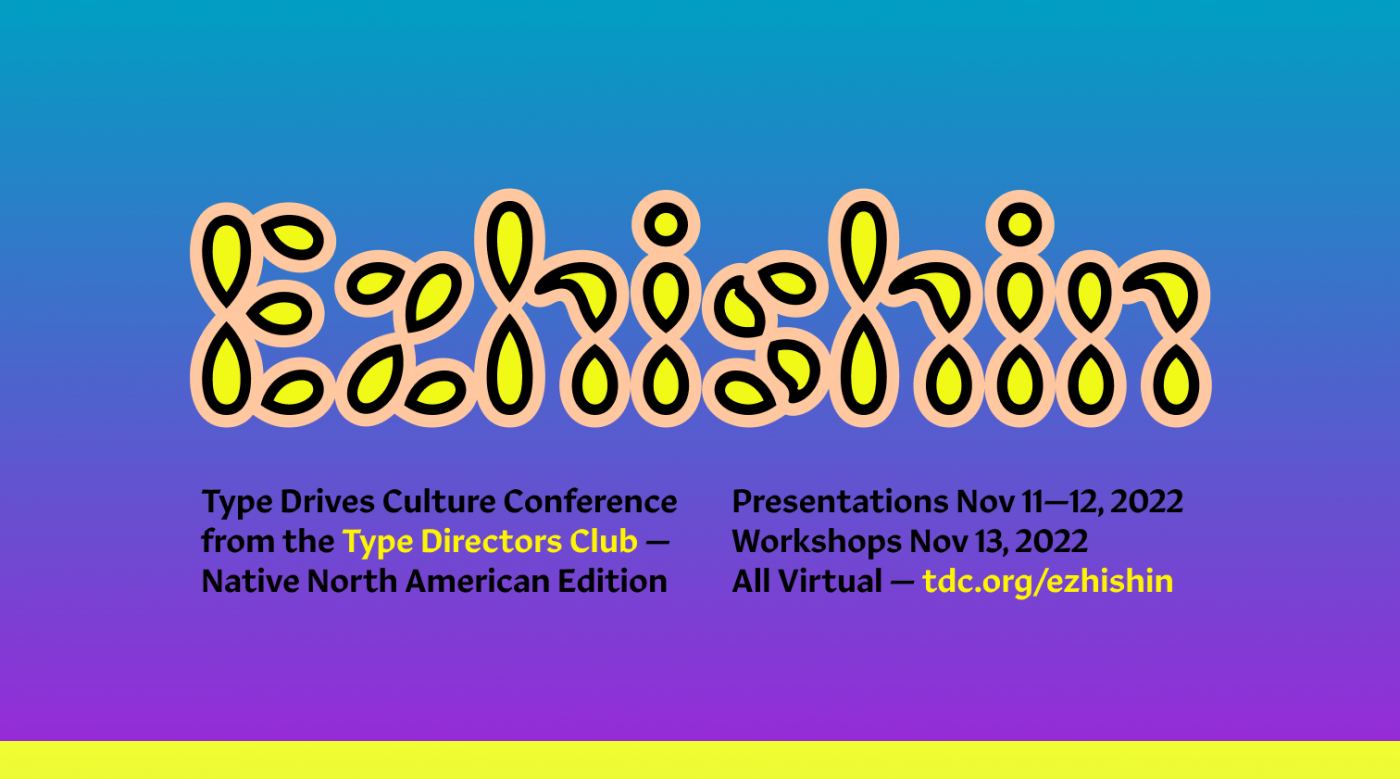
El pasado 11-12 de noviembre el evento EZHISHIN, nos permitió descubrir los desafíos y triunfos que implican diseñar tipografía para lenguas indígenas, el proceso de revivir un idioma o incluso cuestionar el impacto del colonialismo en el diseño y la percepción que tenemos sobre nuestra realidad. Cada presentación es única y generará debates que invitarán a la reflexión, desafiando la sabiduría convencional e inspirando nuevas ideas. Desde el 1 de febrero y gracias al patrocinio de Google, los videos están disponibles para que todos los vean en línea. Te invito a que te prepares para ampliar tu comprensión del poder del diseño y el papel que desempeña en la configuración de nuestro mundo.
EZHISHIN, fué un evento organizado por el Type Directors Club, en cabeza de Neebinnaukzhik Southall quien además de pertenecer a la comunidad Chippewas de Rama de las Primeras Naciones es diseñadora gráfica, artista, fotógrafa y escritora se especializa en trabajar con comunidades indígenas, y Ksenya Samarskaya, la recientemente nombrada directora general de TDC.
A continuación presento lo que para mi fueron las charlas que más cautivaron mi atención de este encuentro, pero no te confíes solo de mi criterio, todos las conferencias son valiosas y cada una está cargada de un gran contenido de valor, por tanto te invito a que te sumerjas en los demás videos que no hayan salido en esta pequeña lista:
The web of text by John Hudson
Tipo de charla: Typographic Design
Podría describir esta relatoría como si Carl Sagan —gran narrador de historias— hubiera regresado para hablarnos sobre el universo tipográfico, solo que ahora está encarnado por John Hudson. Esta disertación busca contarnos de la manera más sencilla posible qué pasa con nuestras tipografías cuando queremos escribir con ellas a la vez que resuelve dudas fundamentales como ¿qué es UNICODE?, ¿Cuál es su historia? ¿Cómo funciona? y porqué aquellos que quieran compartir o componer textos en lenguas particulares necesitan estar dentro del estándar. Para aquellos que se inician en el mundo del diseño de tipografías esta narración puede resultar muy iluminadora. En todo caso esta presentación puede llevarnos a cuestionamientos sobre nuestro quehacer tipográfico y cómo enfrentarnos al estándar UNICODE y pensar cómo podemos hacer la tarea más simple a nuestros usuarios. En fin, una charla clara, simple y directa frente a una parte fundamental —no tan conocida— que quizás abre un mundo de preguntas sobre inclusión.
Sobre la persona conferenciante
John Hudson es cofundador de Tiro Typeworks, una fundición de fuentes digitales que se especializa en tipografía multilingüe personalizada para publicaciones e informática. Es colaborador del estándar Unicode, el grupo de trabajo W3C Webfonts y los grupos de trabajo de diseño y variaciones de OpenType.
Drawing the Cherokee Syllabary and Type Design as Cultural
Por Chris Skillern
Tipo de charla: Diseño Tipográfico
Esta charla es un viaje de ida y regreso donde Chris nos lleva por todo un recorrido sobre cómo transformar nuestras inquietudes personales, culturales y profesionales en algo significativo. Del mismo modo el diseñador nos expone las dificultades que desde su perspectiva supone desarrollar una fuente tipográfica para la lengua Cherokee, y cómo los proyectos evolucionan cuando el diseñador tipográfico intersecta esta nueva duda con sus estudios en el aprendizaje de la lengua. Recomiendo especialmente esta charla a aquellos que estén en el camino del diseño de fuentes para el Cherokee o lenguas indígenas, hay motivaciones potentes que pueden inspirarlos aquí.
Sobre la persona conferenciante
Pertenece a la Nación Cherokee
Chris Skillern es diseñador tipográfico y ciudadano de la Nación Cherokee de Tulsa, Oklahoma, donde vive con su esposa e hija. Como miembro de la clase de graduados de 2021 de Type West, el programa de certificado de posgrado en diseño tipográfico de Letterform Archive, su proyecto final fue una familia tipográfica que consta de tres estilos destinados a libros infantiles que admiten tanto el alfabeto latino como el silabario cherokee.
By the Sun and the Moon – Shaping a Sovereign Syllabary Bobby por Joe Smith III
Tipo de charla: Diseño Gráfico
Nuestras herramientas, recursos, lenguajes y formas han sido moldeadas por una clase privilegiada con una manera de ver el mundo. Esta charla nos muestra los procesos, conflictos e inquietudes que han puesto sobre la mesa un tema tan transversal como la decolonización del Diseño. Pero, ¿Qué quiere decir decolonizar el Diseño? y ¿Qué necesitamos para identificar y entender las herencias que nos ha dejado la colonización? Son preguntas y respuestas muy fuertes que atraviesan la historia cultural norteamericana por completo y que seguramente moverá muchos pensamientos y emociones. La colonización es un cuestionamiento profundo a nuestro sistema de valores y la manera como nos han enseñado a percibir el mundo. En este caso, el Diseño sirve como herramienta de cuestionamiento a través del cual se exige y se lucha, todo este discurso está atravesado de la experiencia y los procesos de diseño de nuestro invitado.
Sobre la persona conferenciante
Pertenece a la comunidad Lakota
Bobby Joe Smith III es un diseñador gráfico y media artist negro y Lakota (Hunkpapa y Oohenumpa). Su práctica creativa tiene sus raíces en los movimientos decoloniales y abolicionistas en curso liderados por comunidades indígenas en Turtle Island y en toda la diáspora negra. Tiene un MFA en Diseño Gráfico de la Escuela de Diseño de Rhode Island (RISD), un título de posgrado en Diseño Gráfico del Maryland Institute College of Art (MICA) y un B.A. en Filosofía y Ciencias Políticas de Middlebury College.
Design & Visual Impact of Osage Orthography & the Utilization of Stencils in the classroom por Dr. Jessica Moore Harjo Otoe-Missouria, Osage, Pawnee
Tipo de charla: Diseño Gráfico/Investigación
¿Qué podemos hacer para traer a la vida una lengua que está en riesgo de desaparecer? Aquí podemos ver todo el proceso de normalización de la lengua, creación de un sistema de escritura y desde luego una tipografía que permita escribir en la computadora. Es muy interesante ver como poco a poco la ortografía y las reglas gramaticales se van ajustando según las convenciones y acuerdos a los que llega la comunidad, lo que nuevamente demuestra que el trabajo del tipógrafo es una pequeña parte del proceso y este se integra a un equipo y una comunidad activa. Es emocionante ver como esta incesante búsqueda de recursos pedagógicos permite desarrollar nuevos ejercicios de aplicación de la tipografía creada, transformándose en una herramienta pedagógica para la enseñanza-aprendizaje del Osage.
In conclusion, EZHISHIN presents a large series of readings that seek to provide evidence of the efforts of researchers, communities, designers, and the social ecosystem that works on typography for Native languages of North America. May this small text serve as a guide to navigating all the conversations and other videos of the congress.